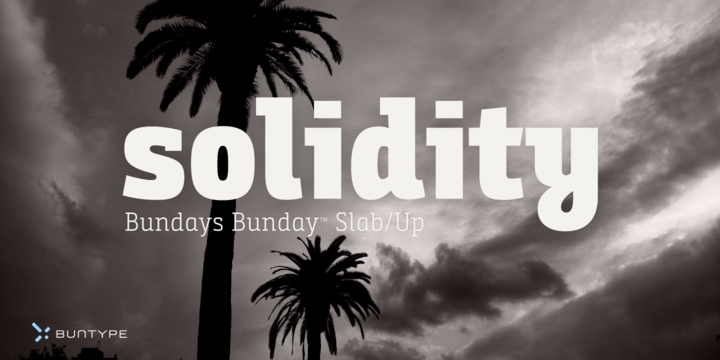
Bunday Slab Font Family – Fonte Grátis
Bunday Slab Font Family
A Bunday Slab Font Family oferece uma experiência visual única para designers que buscam fontes modernas e atraentes. Hamilton é o designer responsável pelo lançamento desta família de tipos, composta por três estados distintos: um tipo de serif grosso e distinto, uma caligrafia delicada em itálico e uma versão estável com a mesma corretaza do original. As formas base contemporâneas, claras e abertas de Bunday Slab garantem que todas as suas variações sejam espaçadas uniformemente e possuam um tom claro e legível. Além disso, foram feitas notáveis adições manuais para a higienização dos conjuntos de entrelinhas, garantindo uma aparência perfeita em qualquer formato de mídia. Esta família é ideal tanto para aplicações comerciais quanto para projetos que buscam um estilo moderno e versátil.